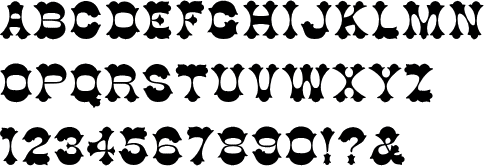
| この書体は「Cottonwood 」という名前で1991年にデジタル化され、Adobe 社のオリジナル書体となっていますが、実は
Darius Wells がデザインし、1854年にリリースされたものです。 1971年にリリースされた
Photo-Lettering 社のカタログでは、「Grover Xenotype」という名称で紹介されています。 |
Gothic Tuscan Italian |
| Designers |
: |
Darius Wells |
|
| Year |
: |
1854 |
|
| Foundry |
: |
Wells & Webb |
|
| Digital |
: |
Cottonwood |